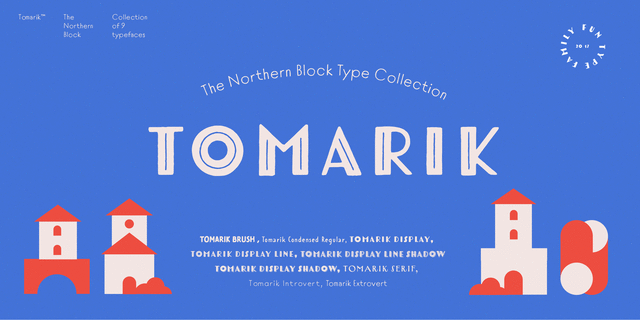
Контрастный гротеск в стиле ар деко, нарисованный вручную – часть яркой коллекции рукописных шрифтов Томарик. Игривое дополнение любого творческого проекта. Шрифтовой набор, собранный для работы по принципу «выбирай и смешивай», он предлагает большое разнообразие стилей и характеров. Томарик содержит девять различных начертаний с латиницей и кириллицей и включает функции OpenType, такие как верхние и нижние индексы и дроби. Шрифт разработала Мария Пигулевская в 2017 году. Tomarik™ является торговой маркой компании The Northern Block.
Функции начертания Tomarik Display RegularПрименение в макете:
журнал, комикс, плакат, реклама, обложка, меню, вывеска, открытка, поздравление, этикетка, упаковка, афиша, анимация, мультфильм, стенгазета Тип носителя:
Ассоциации c начертанием Tomarik Display RegularКачества и характер:
оригинальный, выразительный, праздничный, радостный, позитивный, мотивирующий, детский, наивный, милый, артистичный, добрый, музыкальный, ритмичный, игривый, веселый, интересный, задорный, характерный, приветливый, прикольный, дружелюбный, добродушный, затейливый, смешной, самобытный, неординарный, мажорный, инфантильный, легкомысленный, хитрый, динамичный, странный, улыбчивый, счастливый, творческий, симпатичный, тусовочный, остроумный, забавный, заметный, броский, яркий, театральный, демонстративный, винтажный, активный, круглый, треугольный, здоровый, громкий, ностальгический, рукотворный, приятный, ламповый, мультяшный, школьный
интерьер, развлечения, кафе, отдых, аттракцион, город, праздник, коктейль, сувенир, игра, лагерь, подарки, магия, музыка, канцтовары, детская книжка, приключения, анимация, мультфильм, день рождения, каникулы, юмор, наклейка, стикер, вечеринка, кинотеатр, телевидение, шоу, туризм, кино, цирк, ярмарка, реклама, театр, фокусник, комедия, кофе, паровоз, шоколад, торговля, игрушка, казино, детский сад, завтрак, дача, сок, селфи Стилистика:
Особенности семейства Tomarik DisplayХит десятилетия:
Хит 1930-х |